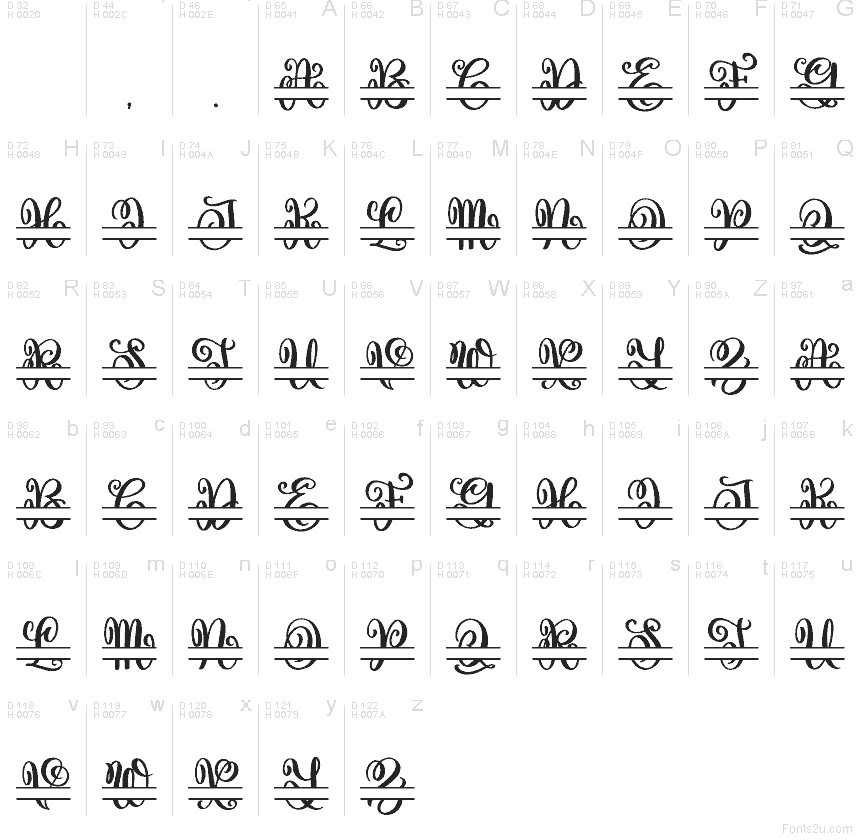
Vase Monogram di Abo Daniel è un font decorativo display gratuito, caratterizzato da tratti alti e avvolgenti, riccioli specchiati e un ritmo che richiama i monogrammi, perfetto per iniziali ricercate. Le forme si elevano e si intrecciano attorno a una solida linea orizzontale, conferendo al design una struttura quasi emblematica, ben lontana da un semplice alfabeto.
Vase Monogram è ideale per monogrammi di nozze, intestazioni di inviti, loghi, articoli di cancelleria e titoli decorativi in cui una singola lettera o una parola breve richiedano un tocco di eleganza. Le sue forme curve e l'impostazione formale sono perfette anche per certificati, etichette di packaging e branding boutique che necessitano di un tocco ornamentale calligrafico.
VASE MONOGRAM